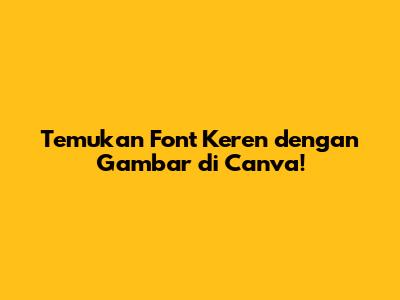
- Meningkatkan Daya Tarik Visual: Font yang tepat akan membuat desain kalian terlihat lebih profesional dan menarik perhatian.
- Memperkuat Identitas Merek: Penggunaan font yang konsisten akan membantu membangun identitas merek yang kuat dan mudah diingat.
- Meningkatkan Keterbacaan: Font yang baik akan memastikan bahwa pesan kalian mudah dibaca dan dipahami oleh audiens.
- Meningkatkan Keterlibatan: Desain yang menarik akan meningkatkan keterlibatan audiens, sehingga mereka lebih tertarik untuk melihat dan berinteraksi dengan konten kalian.
- Siapkan Gambar Referensi: Hal pertama yang perlu kalian lakukan adalah menyiapkan gambar referensi. Gambar ini bisa berupa screenshot dari desain yang kalian sukai, logo merek tertentu, atau bahkan foto tulisan tangan. Semakin jelas gambar referensi yang kalian miliki, semakin mudah Canva mengidentifikasi font yang digunakan.
- Unggah Gambar ke Canva: Buka Canva dan buat desain baru atau buka desain yang sudah ada. Unggah gambar referensi kalian ke dalam desain tersebut. Pastikan gambar sudah terunggah dengan sempurna.
- Gunakan Fitur "Font Finder" atau "Font Identifier" (Jika Tersedia): Canva terus mengembangkan fitur-fiturnya. Beberapa versi Canva mungkin sudah memiliki fitur Font Finder atau Font Identifier yang secara otomatis dapat mengidentifikasi font dalam gambar yang kalian unggah. Jika fitur ini tersedia, gunakanlah! Biasanya, kalian hanya perlu mengklik gambar, lalu Canva akan mencoba mengidentifikasi font yang digunakan.
- Manfaatkan Alat Pihak Ketiga (Jika Fitur Internal Tidak Tersedia): Jika Canva kalian tidak memiliki fitur Font Finder atau Font Identifier, jangan khawatir! Kalian bisa menggunakan alat pihak ketiga yang dirancang khusus untuk mengidentifikasi font dari gambar. Beberapa alat populer yang bisa kalian coba adalah:
- WhatTheFont: Alat ini sangat populer dan mudah digunakan. Kalian hanya perlu mengunggah gambar, dan WhatTheFont akan menampilkan daftar font yang mirip dengan yang ada di gambar.
- Fontspring Matcherator: Alat ini menawarkan fitur yang lebih canggih, termasuk kemampuan untuk membandingkan font dengan koleksi font yang luas.
- Identifont: Alat ini menggunakan serangkaian pertanyaan untuk membantu kalian mengidentifikasi font berdasarkan ciri-ciri visualnya.
- Periksa Hasil dan Pilih Font yang Cocok: Setelah menggunakan fitur Font Finder atau alat pihak ketiga, kalian akan mendapatkan daftar font yang mirip dengan yang ada di gambar referensi kalian. Periksa hasilnya dengan cermat, dan pilih font yang paling cocok dengan gaya desain kalian. Perhatikan juga lisensi font sebelum menggunakannya untuk keperluan komersial.
- Terapkan Font di Desain Canva Kalian: Setelah menemukan font yang tepat, sekarang saatnya untuk menerapkannya di desain Canva kalian. Pilih teks yang ingin kalian ganti fontnya, lalu pilih font yang sudah kalian identifikasi dari daftar font di Canva. Sesuaikan ukuran, warna, dan gaya font agar sesuai dengan tampilan desain kalian.
- Perhatikan Gaya Font: Apakah font tersebut serif, sans-serif, script, atau display? Setiap gaya font memiliki karakteristik visual yang berbeda dan cocok untuk berbagai jenis desain.
- Perhatikan Keterbacaan: Pastikan font yang kalian pilih mudah dibaca, terutama jika kalian menggunakan font tersebut untuk teks berukuran kecil atau teks dalam jumlah banyak.
- Perhatikan Karakteristik Visual: Perhatikan bentuk huruf, jarak antar huruf, dan berat font. Apakah font tersebut terlihat modern, klasik, formal, atau kasual?
- Cocokkan dengan Gaya Desain Kalian: Pilih font yang sesuai dengan gaya desain kalian secara keseluruhan. Jika kalian membuat desain untuk merek yang modern, kalian mungkin ingin menggunakan font sans-serif yang bersih dan sederhana.
- Perhatikan Lisensi Font: Pastikan kalian memiliki lisensi yang tepat untuk menggunakan font yang kalian pilih, terutama jika kalian menggunakan font tersebut untuk keperluan komersial.
- Gunakan Kombinasi Font: Jangan takut untuk menggabungkan beberapa font dalam desain kalian. Gunakan satu font untuk judul dan subjudul, dan font lain untuk isi teks.
- Simpan Font Favorit Kalian: Setelah kalian menemukan font yang kalian sukai, simpan font tersebut di koleksi font favorit kalian agar lebih mudah diakses di kemudian hari.
Hai, guys! Pernahkah kalian terpukau dengan desain keren dan bertanya-tanya, "Font apa sih yang mereka gunakan?" Nah, jangan khawatir! Sekarang, kalian bisa dengan mudah menemukan font yang cocok dengan gambar di Canva. Gimana caranya? Yuk, kita bedah tuntas! Artikel ini akan membimbing kalian langkah demi langkah, sehingga kalian bisa menemukan font yang pas untuk proyek desain kalian.
Memahami Pentingnya Pemilihan Font yang Tepat
Pemilihan font yang tepat adalah salah satu kunci utama dalam desain grafis. Font yang dipilih tidak hanya berfungsi sebagai tulisan, tetapi juga menyampaikan pesan visual yang kuat. Bayangkan, kalian sedang membuat poster promosi untuk acara musik. Font yang kalian gunakan akan menentukan kesan pertama yang diterima oleh audiens. Jika kalian memilih font yang salah, pesan yang ingin kalian sampaikan bisa jadi tidak tersampaikan dengan baik, atau bahkan terlihat kacau.